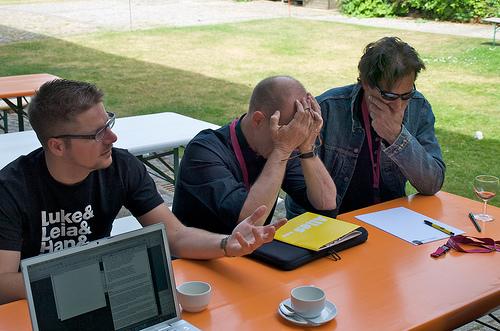
typo berlin – wer geht hin?
der 29.5. ist nicht mehr allzu weit und ich wollte mal in die runde fragen, wer alles zur typoberlin geht?
Sofern mein Flieger rechtzeitig landet, werde auch ich dort sein.
Ich auch! Aber wo ist Berlin? Berlin ... kommt mir irgendwie bekannt vor ... den Rhein runter und am Ende scharf rechts durchs Meer und dann?
... zu Fuß durch Nordfriesland, dann die Ostsee bis etwa Stralsund durchschwimmen und noch ein paar Tage zu Fuß nach Süden.
Etwas viel der Schwimmung für uns Bergler, nicht? Muss ich wohl noch ein paar wasserfeste Nusstorten vorbacken, so als Wegzehrung ...
Schade, dass Berlin so weit wegt.
Wünsche allen Geherinnen und Gehern viele spannende Einsichten!
sag mal robertmichael, ich erinnere mich da an eine aussage, deine schriftmuster jedem zu zeigen, der zur typo kommt :wink:
das ist eine glatte lüge. es sei denn ihr zahlt eintritt dafür,
dann würden microboy und ich uns vielleicht gnädig zeigen ;)
falls übrigens genau zu der zeit, während ich in berlin verweile,
bei henning 'the capitalis k' eingebrochen werden sollte – ich wars nicht!
bei der sammlung würde ich auch schwach werden :biglove:
Und, wie fandet ihr es?
Da sich viele Vorträge nicht um Typo, sondern um Bilder und Fotografie drehten, war nicht alles so wahnsinnig spannend für mich. Aber die hochinteressanten Fachgespräche am Rande der Typo haben das locker wieder wettgemacht. :D
Ein erwartungsgemäßes Highlight war natürlich Altmeister Ed Beguiat. Unerwartetes Highlight war David Berlow (Font Bureau), der auch in Natura so gewitzt und scharfsinnig rüber kommt, wie in seinen Typophile-Beiträgen.
Der German-Type-Versaleszett-Anstecker an meinem Sakko inspirierten ihn und Mr. Spiekermann, über die perfekte Form des Versalszetts nachzudenken:
Gefunden wurde sie an diesem Tage allerdings trotzdem nicht.
Irgendwann kann ich es mir leisten oder meine Geldgeber überzeugen da hinzufahren :)
Aus der Ferne habe ich auch den Eindruck gehabt dass Schrift und Typografie etwas "im Hintergrund" gestanden haben. Aber allein das Dortsein ist bestimmt inspirierend.
Da haben sich die Pins doch gelohnt. :wink: Kann es sein, daß Erik bei diesem Theama leicht genervt war/ist? Jetzt muß er als guter TypoDeutscher auch noch das versale Eszett erklären.
Kann es sein, daß Erik bei diesem Theama leicht genervt war/ist?
Keine Ahnung. Ich werd lieber nicht mutmaßen oder versuchen, seine Worte aus dem Gedächtnis zu wiederholen. Vielleicht meldet er sich ja bei Gelegenheit noch hier zu Wort. Jedenfalls war der komplette Tisch kontra Versaleszett bzw. kontra der momentan von den meisten favorisierten Form.
Dieses Bild von Stephen Coles fängt die Stimmung noch besser ein: :lol:
Ja, das Bild sagt viel. Aber gerade weil er dagegen ist, würde mich seine Idee interessieren. Wie sieht das versale Eszett in der Meta, der Unit oder der DB-Type aus? Bei der DB-Type liegt die praktische Anwendung nah.
Da wir alle drei – wie von Ralf bereits angemerkt – einer Meinung waren, weiß ich natürlich noch, wie Erik das sieht. Genervt war er jedenfalls nicht wirklich. Er hält die Idee allerdings für nicht durchsetzbar. Eben aus den einfachen Gründen, dass man aus einer historischen Minuskelligatur, die sich zu einem eigenen Buchstaben entwickelt hat, keine neuen Majuskelbuchstaben machen kann. Es wäre für die Rechtschreibung sicher toll, aber für die Typografie …
Wie auch immer, ich will das Thema hier auch nicht weiter strapazieren, ein Versal-ß wird es in Spiekermannschen Schriften in nächster Zeit wohl nicht geben, in den amerikanischen von Berlow & Co. sowieso nicht.
Und um noch was zum Thema beizusteuern: TYPO war – wie immer – absolut lohnenswert. Trotz Jetlags.
Stephen hat das Foto aufgenommen. Zu sehen sind David Berlow, Erik Spiekermann und ein weiterer anonymer Typoholiker.